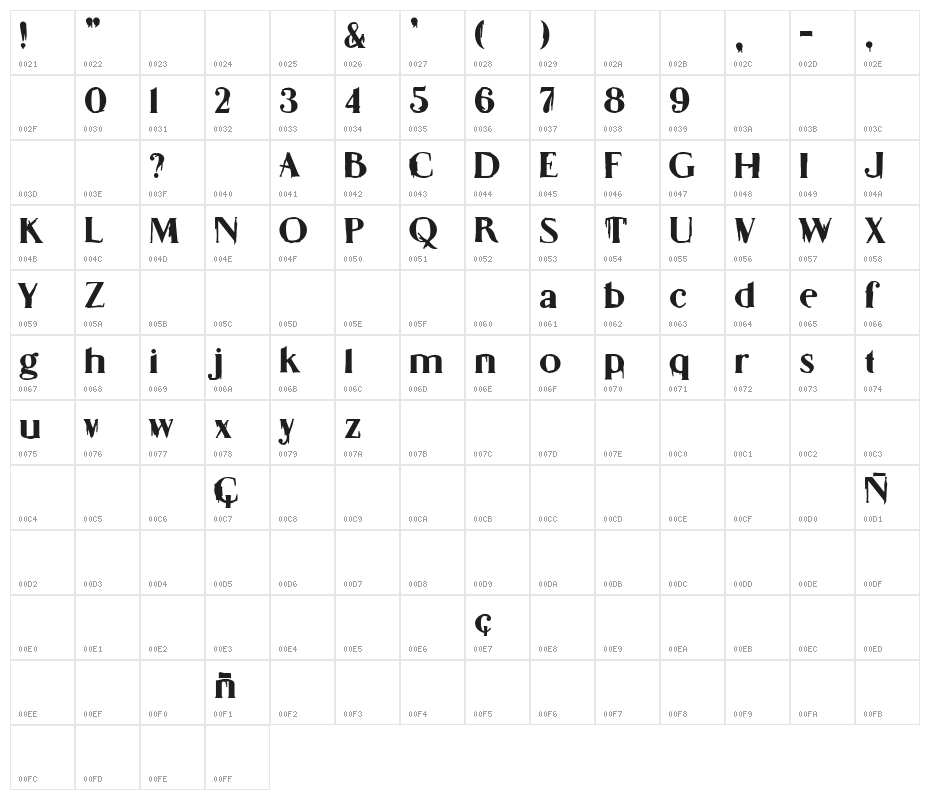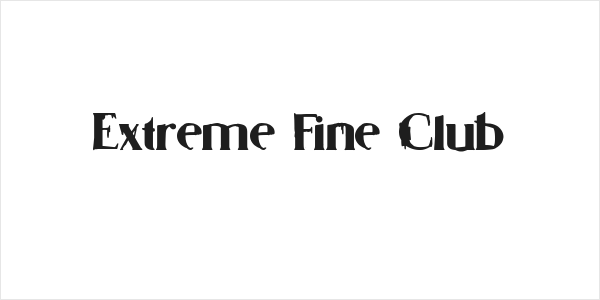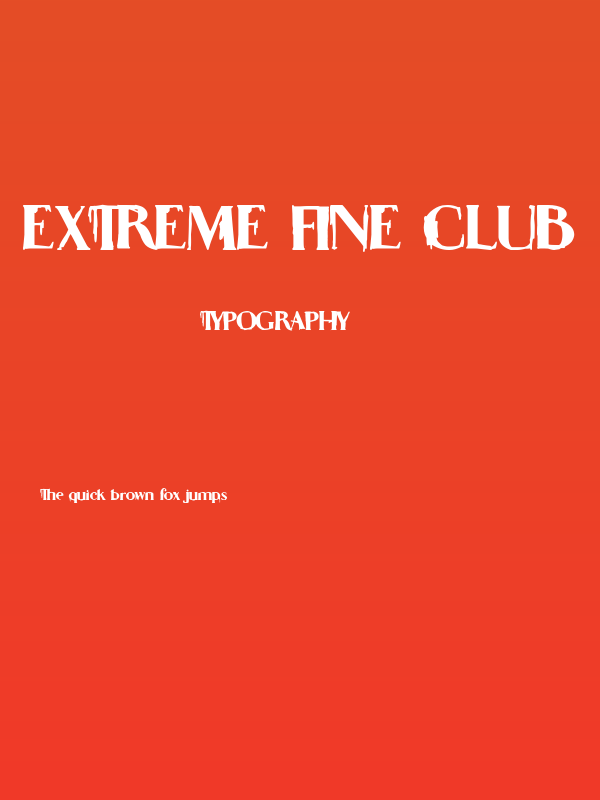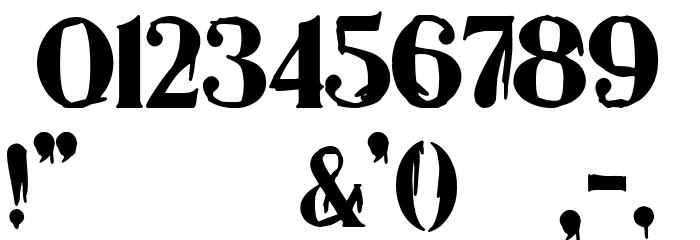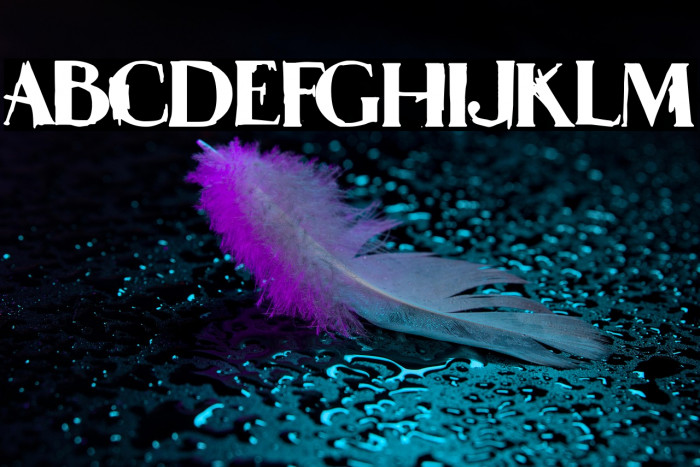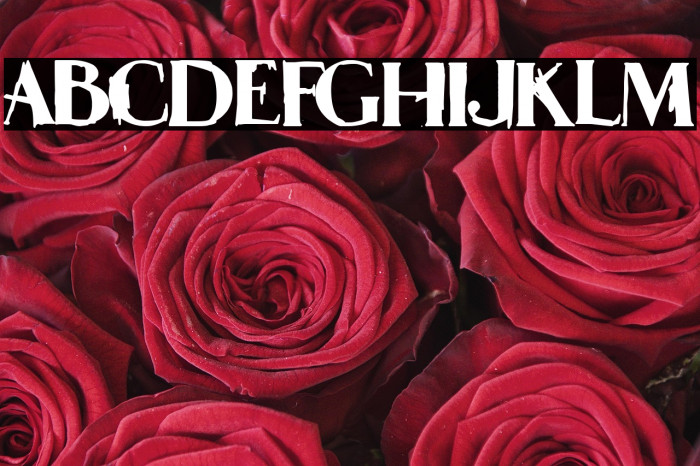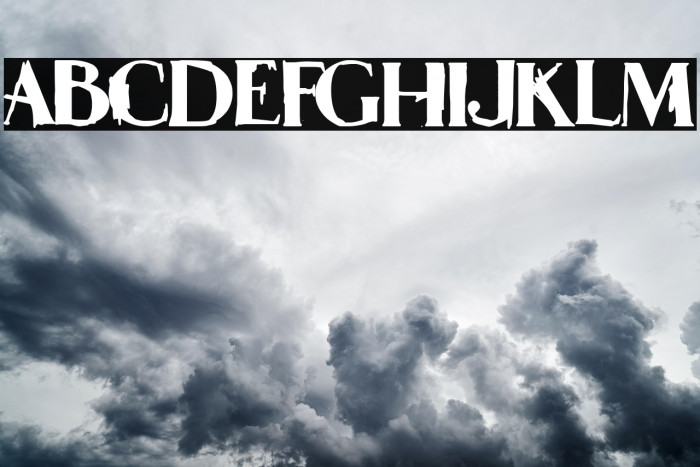
Extreme Fine Club Font
✎ Gothic
| Kategorien | Gothic |
| Gesamtstil | Gothic, Dramatic, Distressed |
| Anwendungsfall | Headlines, Posters, Branding |
| Vorgeschlagene Projekte | Ideal for horror-themed posters, Halloween invitations, gothic book covers, and edgy branding materials. |